Bisnis fashion memiliki banyak pesaing dan terus berubah dengan cepat, penting untuk memiliki desain yang relevan dan menarik. Setiap jenis fashion akan memiliki ciri desain visual yang berbeda dan menyesuaikan citra fashion. Desain brand fashion streetwear seringkali cukup unik dan bold, seperti menggunakan font yang tajam, kaku dan bergaya urban.
Fashion streetwear ini memiliki style pakaian masyarakat urban dengan style kasual dan terinspirasi dari budaya jalanan. Gaya berpakaian streetwear yang berkesan bebas ini akan relevan dengan desain visual yang juga bebas dan bold. Elemen-elemen visual yang digunakan untuk mencerminkan brand fashion streetwear akan tampil bold, kontras, edgy dan trendy.
REKOMENDASI FONT UNTUK BRAND FASHION STREETWEAR
Untuk gaya font yang cocok pada desain brand streetwear biasanya akan tampil bold, unik, nyentrik dan modern. Tipografi yang bold akan digunakan pada desain logo, desain pakaian, poster dan berbagai kebutuhan lainnya. Beberapa font ini bisa dipilih untuk mencerminkan brand streetwear yang kasual dan edgy:
Font Chomsky
Style font black letter akan cocok untuk mencerminkan fashion urban yang kasual dan berkesan trendy. Font blackletter memiliki desain huruf yang unik, tajam, kaku dan lancip. Gaya font ini memiliki serif kecil sab huruf tebal dan lancip.
Bentuk huruf yang geometris menciptakan kesan, kaku, tajam dan berani, cocok untuk mencerminkan fashion jalanan. Jenis font ini juga banyak ditemui untuk menciptakan desain gambar pada fashion streetwear. Tipografi ini bisa mencerminkan bisnis fashion streetwear yang bergaya tajam dan nyentrik.
Font Bree Serif
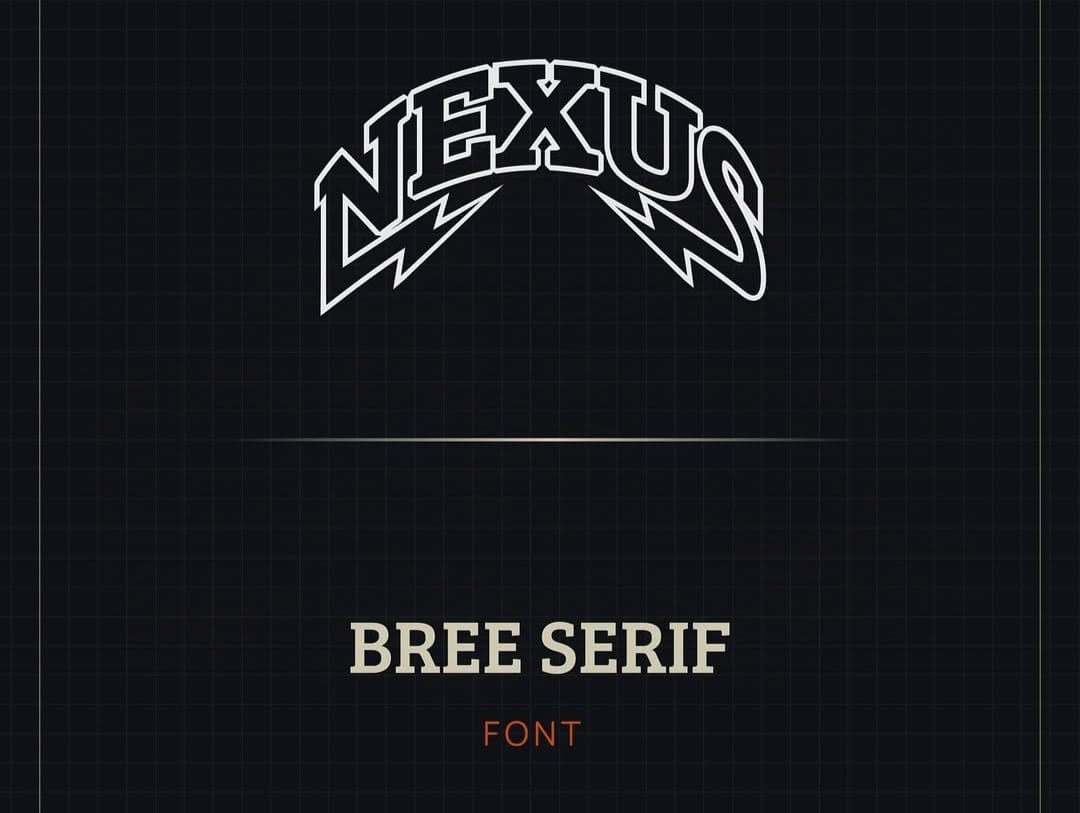
Jenis font yang digunakan untuk mencerminkan identitas brand fashion streetwear seringkali menggunakan huruf tebal. Font yang memiliki huruf akan mencerminkan kesan brand fashion yang berani dan bold. Font slab serif dengan serif kotak yang tebal akan relevan juga dengan brand fashion streetwear.
Penggunaan font slab serif juga banyak ditemui pada desain pakaian streetwear untuk memudahkan teks terbaca. Untuk desain logo brand fashion akan berkesan tegas dan unik. Gaya font tebal dan sederhana ini juga memudahkan untuk dibaca.
Font Dimitri
Selain font serif yang tebal, gaya font bersih dan geometris juga akan cocok untuk desain brand streetwear. Font tebal dan bergaya geometris akan tampil, kaku dan berani seperti font dimitri ini. Penggunaan font tebal yang bersih ini juga memudahkan untuk teks terbaca dengan baik.
Bentuk geometris yang kaku dan tajam akan mencerminkan style desain modern yang populer. Brand streetwear sering menggunakan gaya desain yang mencerminkan budaya jalanan saat ini. Meski font tampil bersih tetapi masih mencerminkan kesan eksentrik ala masyarakat urban.
Font Roboto Barethelly Signature
Desain brand streetwear tidak harus menggunakan tipografi yang eksentrik dan unik. Gaya font sederhana dan bersih juga bisa tampil menarik, style font modern bisa dimodifikasi dengan unik. Font sans serif modern misalnya, gaya huruf yang tebal bisa mencerminkan kesan brand yang tajam dan berani.
Font roboto yang tebal dapat divariasikan tata letaknya agar mencerminkan brand streetwear dengan baik. Kombinasi font roboto yang tebal dan font script tipis tersebut menciptakan tampilan yang trendy dan menarik. Style font modern bisa mencerminkan bisnis fashion streetwear modern yang trendy.
STYLE DESAIN VISUAL BRAND STREETWEAR
Secara umum fashion streetwear memiliki pakaian bergaya hip-hop, skateboard, dan gambar grafiti. Gaya fashion ini memiliki style pakaian yang disukai anak muda urban sehingga bergaya modern dan kasual. Ciri khas brand ini memiliki desain bold, warna kontras hingga desain yang trendy dan populer.
Tampil Bold dan Beda
Tipografi Berani dan Tebal: Jika diperhatikan secara keseluruhan brand streetwear sering menggunakan font tebal, kaku dan tajam. Penggunaan font tegas yang di custom dan akan menciptakan dampak visual yang kuat. Desain brand streetwear sering menggunakan jenis font tebal seperti sans serif, blackletter dan slab serif.
Logo Simpel dan Ikonik: Desain logo untuk brand streetwear seringkali memiliki desain yang minimalis. Logo yang sederhana akan mudah dikenali, diingat namun tetap menonjol. Sering juga logo berbentuk monogram, simbol abstrak dan tipografi yang dimodifikasi dengan unik.
Warna yang Kontras dan Berani
Warna monokrom: Untuk warnanya, desain brand streetwear bisa menggunakan warna monokrom agar tampil estetik dan stylish. Desain brand yang modern dan edgy akan cocok menggunakan warna monokrom hitam putih. Desain visual akan tampil modern dan edgy, yang mana cocok juga untuk tipografi tebal dan tajam.
Aksen Warna Terang atau Neon: Untuk menarik perhatian, desain grafis bisa menggunakan warna terang seperti merah, kuning dan biru. Kombinasi warna kontras akan menarik perhatian.
Pada desain logo, biasanya akan menggunakan elemen-elemen yang besar dan berkesan kuat. Ukuran tipografi yang besar dan tebal akan menciptakan kesan berani dan kuat. Bahkan jika logo digunakan pada ukuran masih memiliki kesan kuat dan tajam.
Desain neand untuk streetwear secara umum memiliki ciri desain yang nyentrik, bebas, kreatif dan bold. Penggunaan elemen visual yang bold dan gambar yang menarik akan mencerminkan budaya urban yang populer. Font untuk desain brand streetwear secara umum memiliki tipografi tebal, kaku, tajam dan bergaya eksentrik.